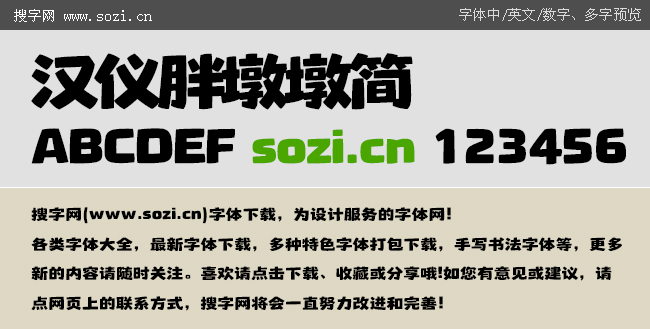
漢儀胖墩墩簡
搜字網(wǎng)給大家提供一款漢儀胖墩墩簡中文字體下載,漢儀胖墩墩簡是一款充滿趣味的藝術字體,筆畫處理突破常規(guī),靈活多變,厚重的字形中凸顯了幾分俏皮,既穩(wěn)重又有趣味,適用于畫冊設計、海報設計、包裝設計等場合使用。(本字體為個人非商用版,如需要商用請聯(lián)系漢儀公司購買版權)